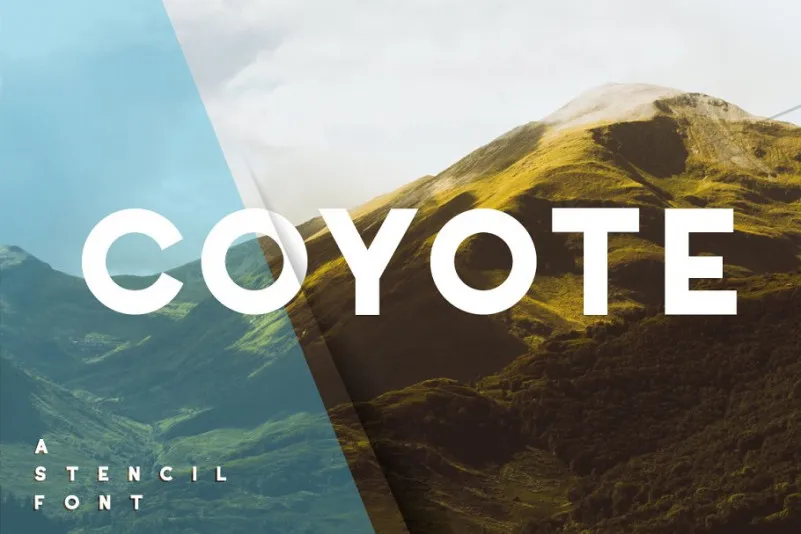
Coyote Font Family – Download Grátis
Esta é uma nova família de fóntes descolada e retro! É perfeito para estilos modernos e criativos que valorizam um estilo urbano. Este conjunto de letras fornece um enfoque alegre, combinando elegância e agressividade com bordas afiadas, ideal para expressar tranquilidade em seus projetos. Além disso, oferece uma alternativa divertida aos padrões normais das letras, permitindo que você crie ideias de marca impecáveis para logotipos, rótulos, camisetas e brochuras. Introduzimos agora a Coyote Retro Font, uma fonte elegante com bordas afiadas para enfatizar o caráter calmo da letra. Não importa se você quer criar um design moderno e inovador ou algo mais descolado, essa família de letras tem espaço para todos os seus ideais criativos e estilos urbanos. Descubra agora porque Coyote é a fonte perfeita para seu próximo projeto!